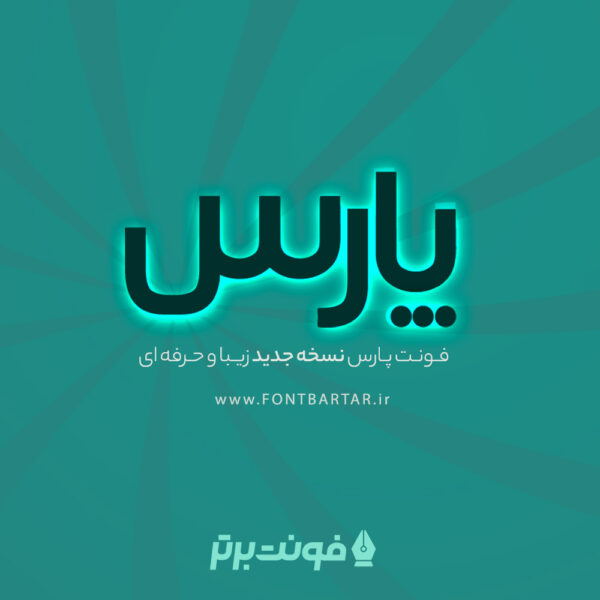
فونت فارسی پارس
Pars Font
فونت پارس | فونت لوگوتایپ و فونت تایپوگرافی
فونت پارس یکی دیگر از فونت های طراحی لوگوتایپ و تایپوگرافی می باشد، فونت فارسی پارس با طراحی حرفه ای و انعطاف پذیر می باشد و این امکان را فراهم می آورد که به راحتی بتوانید حروف را در کنار هم قرار دهید، با خرید فونت فارسی پارس می توانید بدون هیچگونه دانشی لوگو تایپ طراحی کرده و تایپوگرافی های زیبایی انجام دهید و از آن کسب درآمد کنید.
فونت پارس دارای چند وزن است؟
• فونت فارسی پارس در یک وزن می باشد.
فونت پارس از چه زبان هایی پشتیبانی می کند؟
• از زبان فارسی پشتیبانی می کند.
مزایای استفاده از فونت پارس :
• طراحی آسان لوگوتایپ در زمان محدود
• انعطاف پذیر و قابل استفاده در هر طرحی